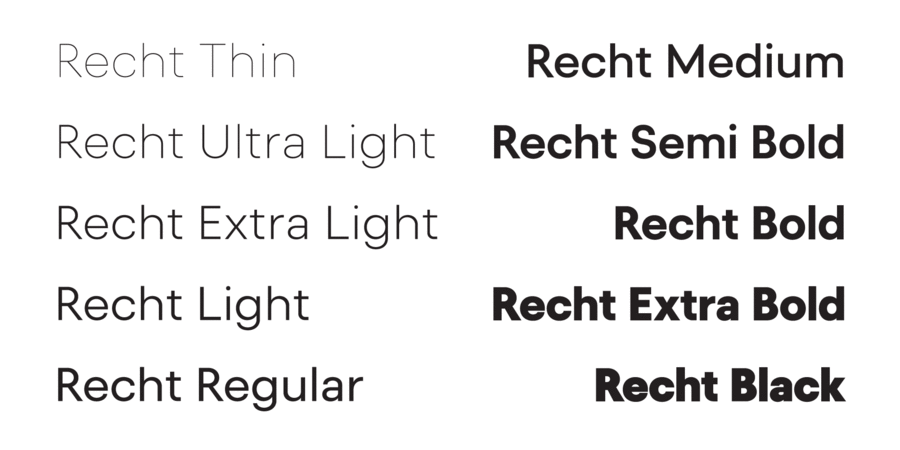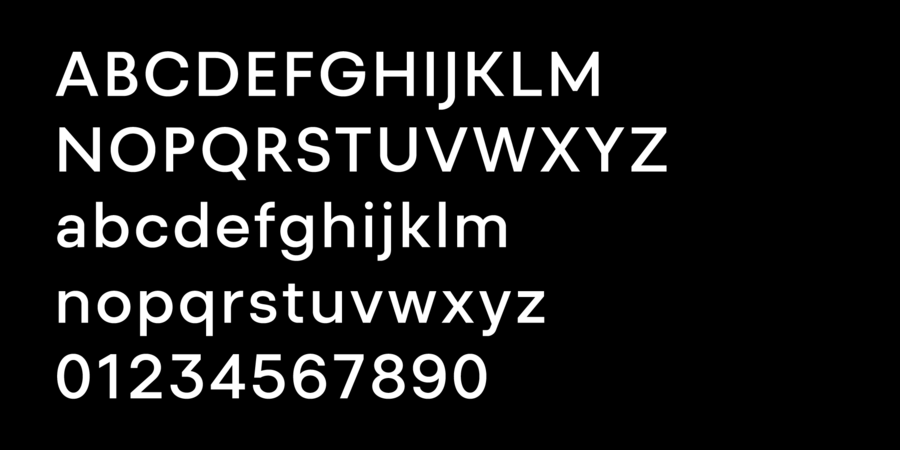
Recht (20 шрифтів)
Опис гарнітури RechtRecht — це геометричний шрифт без засічок, який знаходиться між класичними геометричними шрифтами та неогротесками. Сімʼя містить 10 ваг з відповідними курсивами, кирилицю із включенням української кирилиці та купу функцій OpenType.
Recht має закриту апертуру та є надзвичайно універсальним, чудово працює як у заголовках, так і в довгих абзацах тексту. Для додаткового геометричного або гуманістичного присмаку містить стилістичні сети.
Шрифт розробив Андрій Константинов у 2023 році.
Асоціації з сімейством шрифтів RechtОсобистість і характер гарнітури:
елементарний, мінімалістичний, точний, рівний, статичний, логічний, лаконічний, стійкий, автоматичний, штучний, холодний, інженерний, міський, різкий, чіткий, креслярський, чистий, сучасний, гострий, тонкий, дротяний, скляний, легкий, прохолодний, ясний, невагомий, прозорий, крихкий, модний, худий, делікатний, свіжий, якісний, популярний, глобалізований, глобалістічний, технічний, стабільний, Простий, нейтральний, урбаністичний, твердий, зрозумілий, доступний, правильний, формальний, серйозний, самостійний, відповідальний, західний, діловий, спокійний, помірний, невиразний, універсальний, розумний, стандартний, прагматичний, практичний, надійний, впевнений, машинний, байдужий, комфортний, зручний, непомітний, сильний, переконливий, індустріальний, техногенний, обов'язковий, архітектурний, залізний, сталевий, міцний, авторитетний, важливий, мотивуючий, крутий, залізничний, солідний, амбітний, мужній, суворий, добротний, значний, важкий, потужний, жорсткий, товстий, яскравий, помітний, щільний, тісний, монументальний, активний, грубий, гучний, сміливий, пролетарський, крижаний